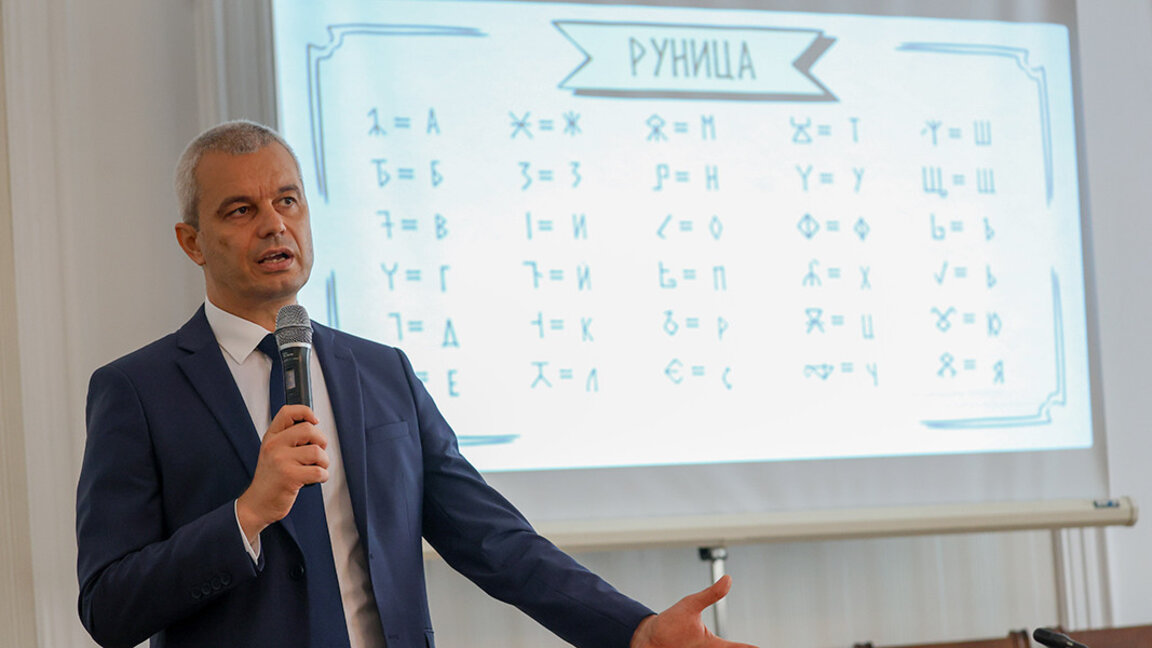
Проект на нов български компютърен шрифт "Руница" представи на пресконференция в парламента лидерът на "Възраждане" Костадин Костадинов. "Решихме да възродим това българско наследство, като направим шрифт, с който да можете да превръщате кирилицата в руница и руницата в кирилица“, обясни Костадинов.
Той припомни, че прабългарските руни са древна писменост на прабългарите, използвана до X век паралелно с кирилицата. За пример той посочи Мурфатларския манастир, намиращ се на територията на днешна Румъния, в който могат да се видят и трите вида българска писменост – глаголица, кирилица и рунически знаци. "Шрифтът ще бъде безплатен, има го на интернет страницата на "Възраждане", където има точни инструкции как да се свали и инсталира", каза Костадинов.